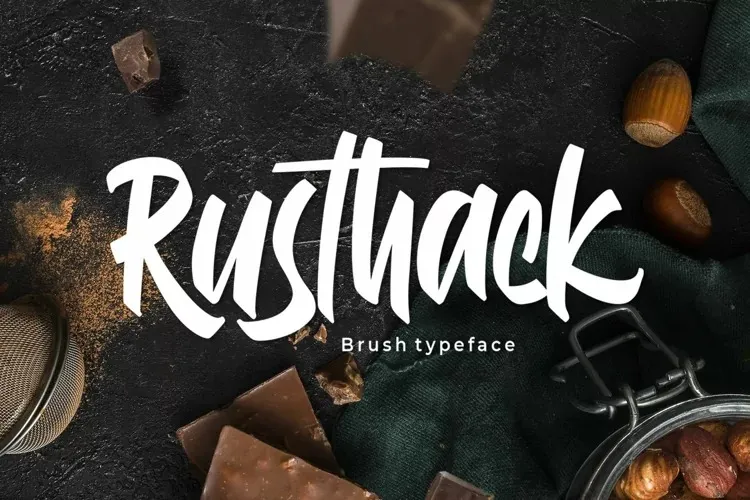
Rusthack Font – Download Grátis
A Rusthack Font é uma fonte script desenvolvida pelo Arterfak Project que captura o espírito forte e expressivo dos traços manuais de uma canetada. Esta elegante fonte adota um estilo casual, mas com uma força bruta que a torna capaz de abraçar os mais variados tópicos de texto sem perder seu charme. Ela vem direto da mão do artesão que o criou, proporcionando traços livres e espessura que dão ao design um toque natural e autêntico. Seja para uso em postagens ou textos legíveis, Rusthack oferece um padrão de escrita instantaneamente reconhecível, ideal tanto para publicações online quanto para aplicações digitais. Através deste design único, o usuário é capaz de estabelecer uma conexão visual forte e contínua em seu conteúdo digital, tornando cada palavra ou frase um elemento importante da narrativa apresentada.